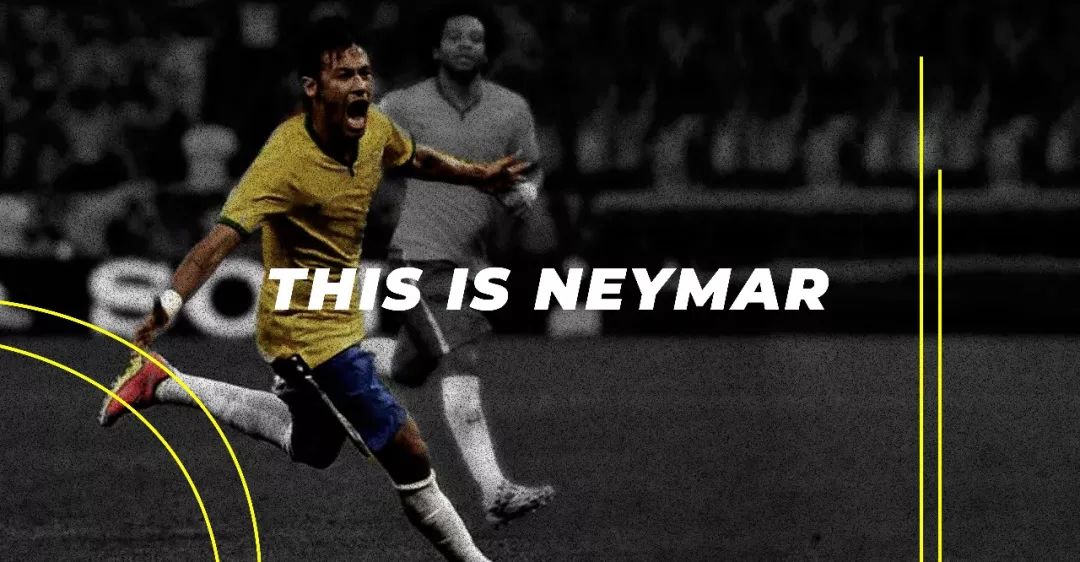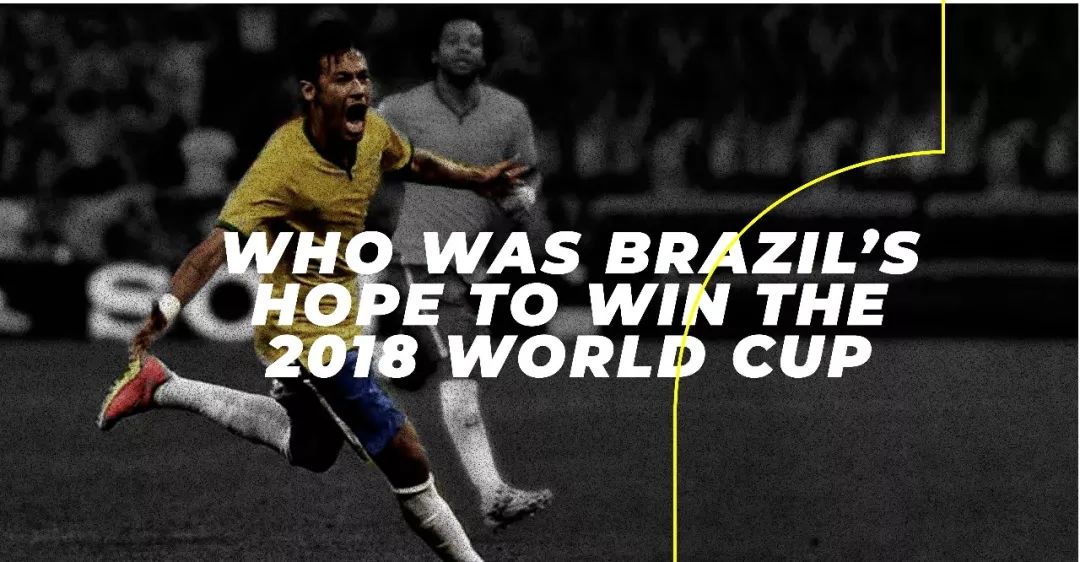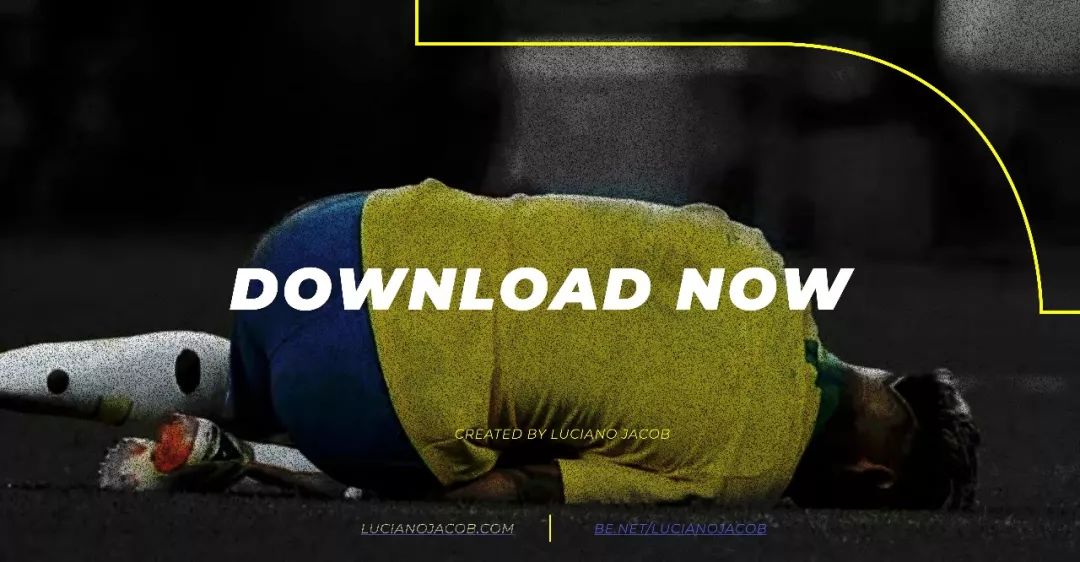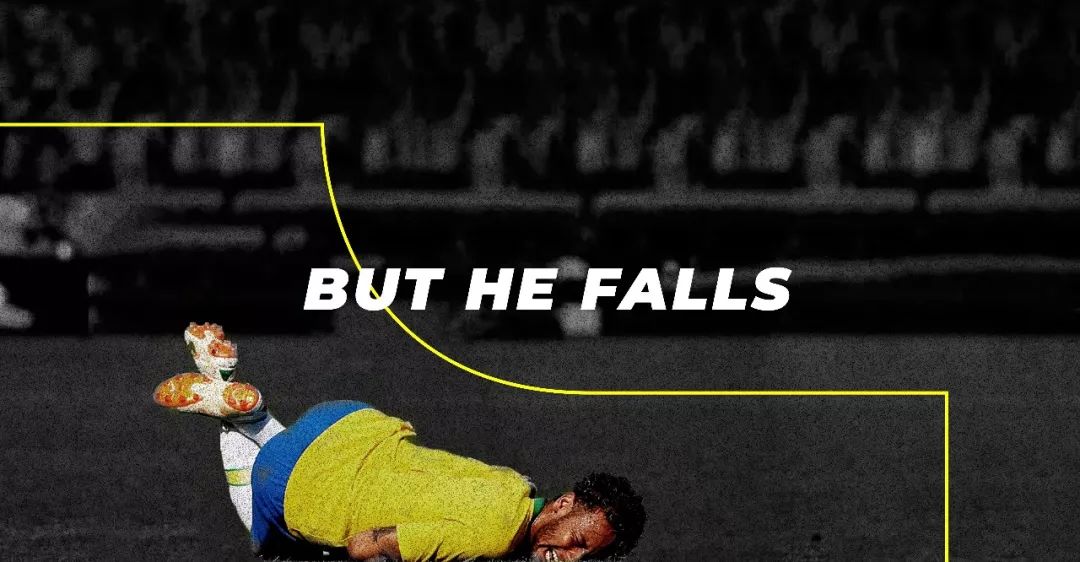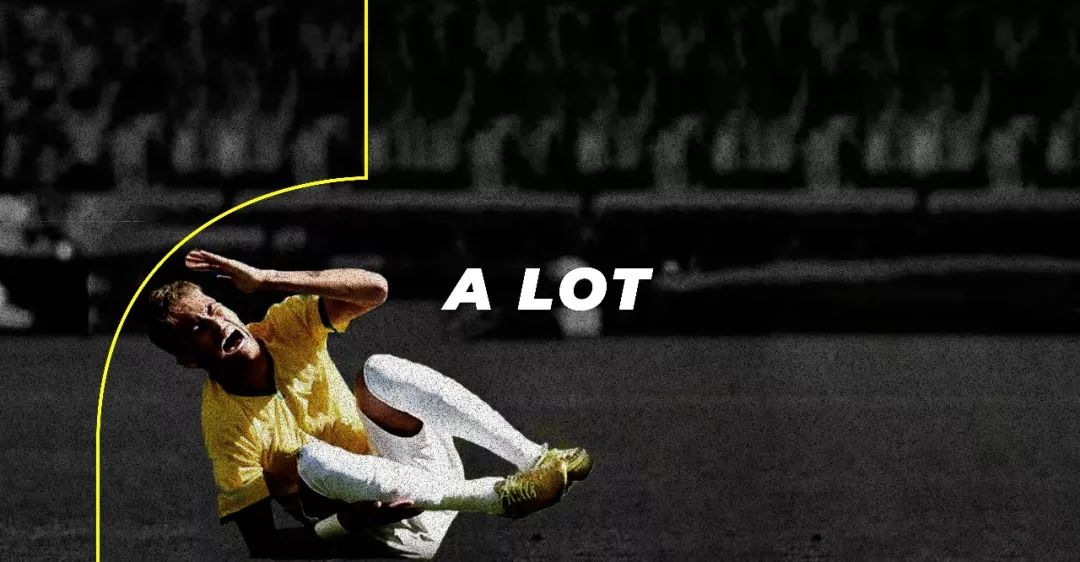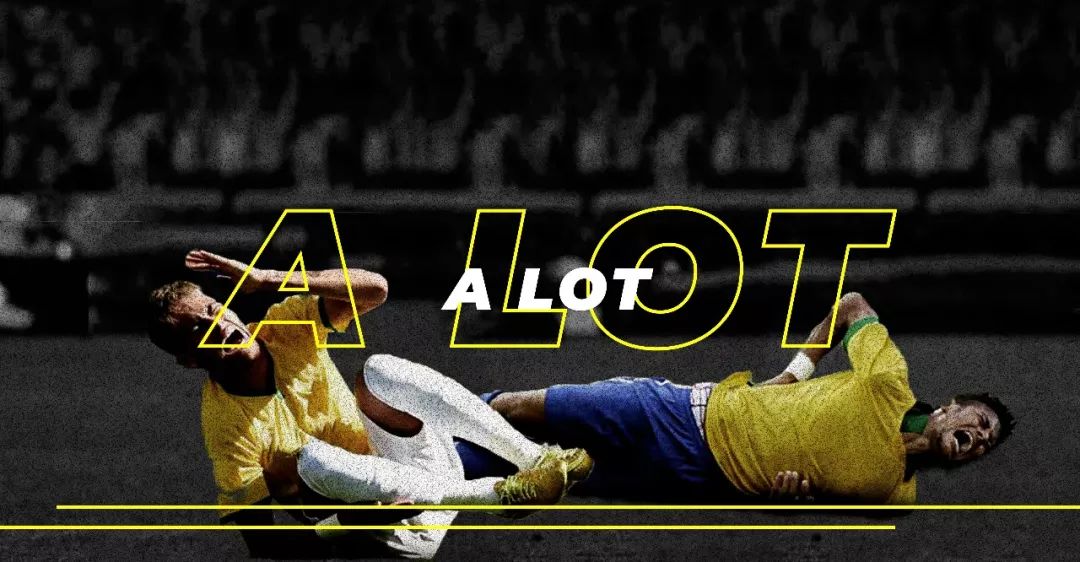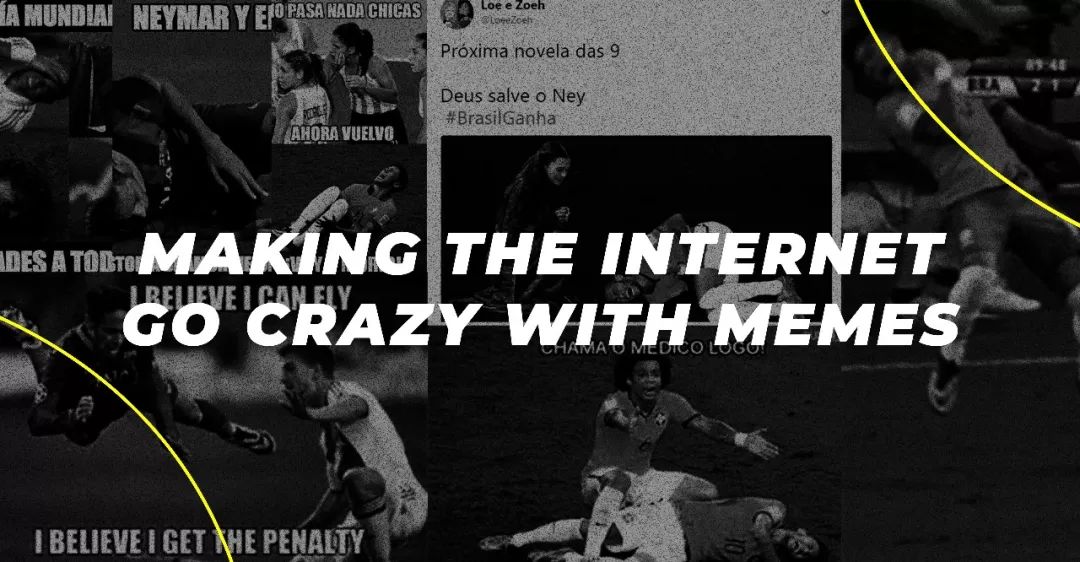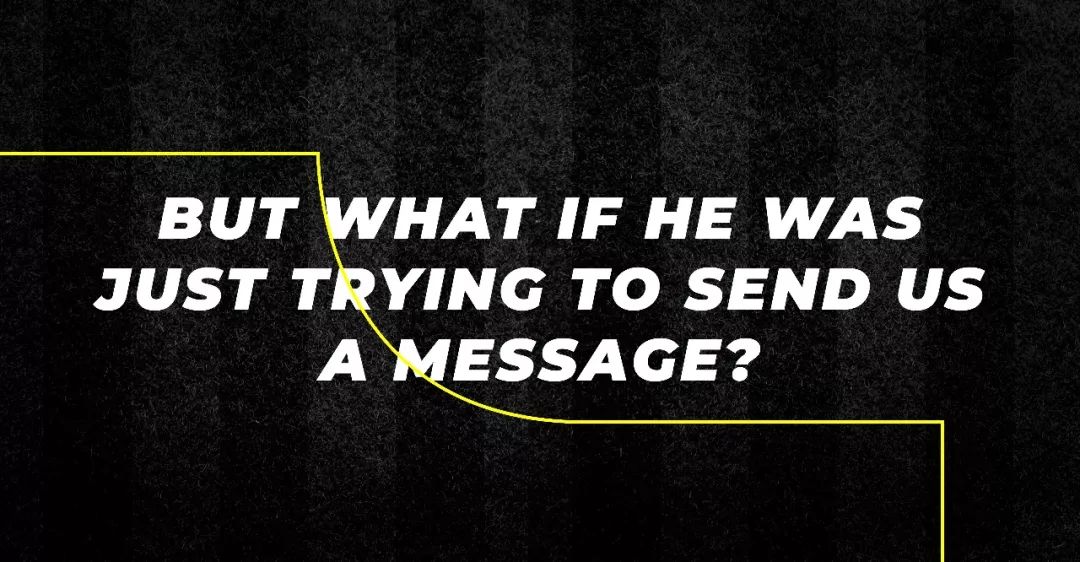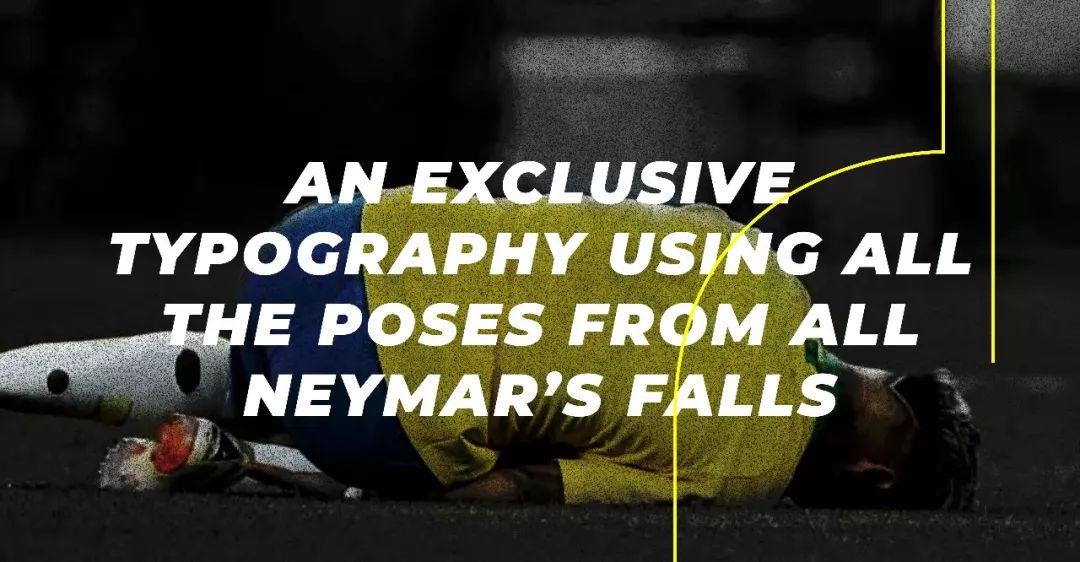
Ney type,使用内马尔滚作出了一套字体图
2018年世界杯的重量级球星内马尔,和梅西、C罗一起离开了俄罗斯,但他在球场上的风姿依旧给我们留下了深刻印象,有些行为也引起了部分争议。但是都不影响内马尔继续火下去。
Mutato公司的设计总监Luciano Jacob用各种内马滚作出了一套字体图:Ney type,而且开放原图供大家下载。内马尔翻滚的姿势刚好凑成了26个字母,十分“传神”。
下面附上设计师的设计理念
这是内马尔
他曾经是巴西队赢得2018年世界杯的希望
但他摔倒了/失败了
(fall有失败和摔倒两个意思,一语双关)
几次
超多次
让整个网络都因他的memes疯狂
但有可能他其实是试着要向我们发送一些讯息呢?
所有的姿势有来自于内马尔的摔倒的姿势
期待2022年
26个字母